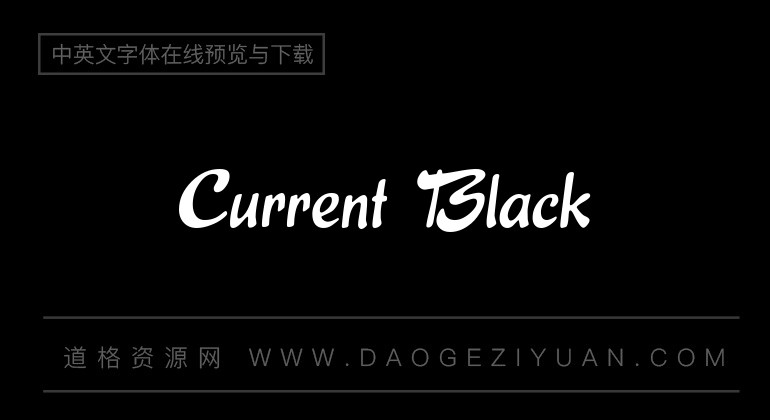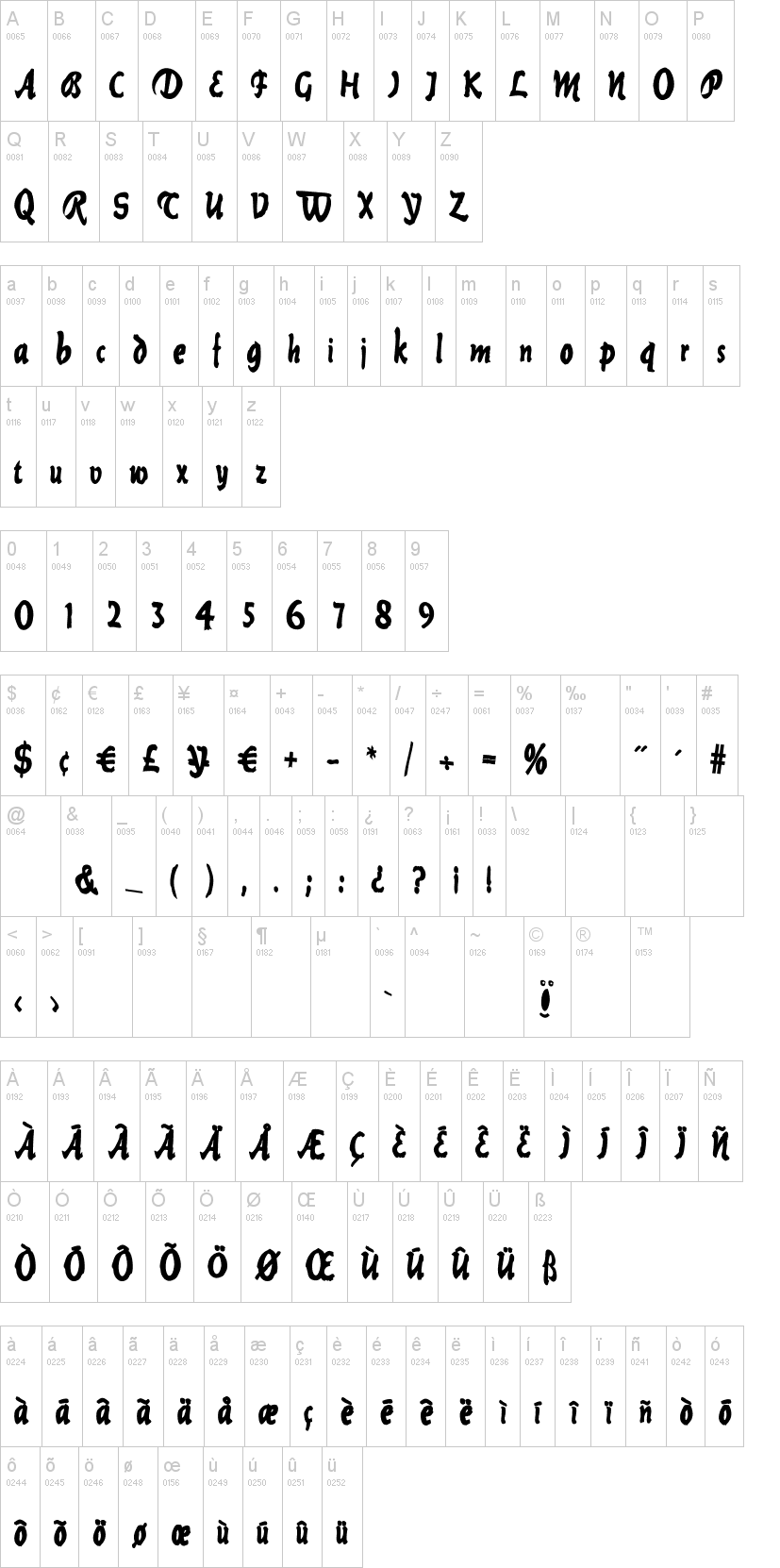
Current Black
? Current Black 是一款由英国设计师Jonny Pinhorn设计的一款多功能性字体。它的特点是简洁、细节丰富、字形结构紧凑,适用于报刊、海报、书籍、电影、品牌标识等多种场景。它拥有超过400个字符,包括多种西欧语言和希腊语,可以满足不同语言的需求。它的字体风格既传统又现代,可以带给用户更多的视觉体验。
Current Black是一款非常不错的手写艺术字体,具有很好的视觉感,适合于文化类的宣传设计、商业类品牌的广告和产品包装设计以及个性化文字排版等较多场景。